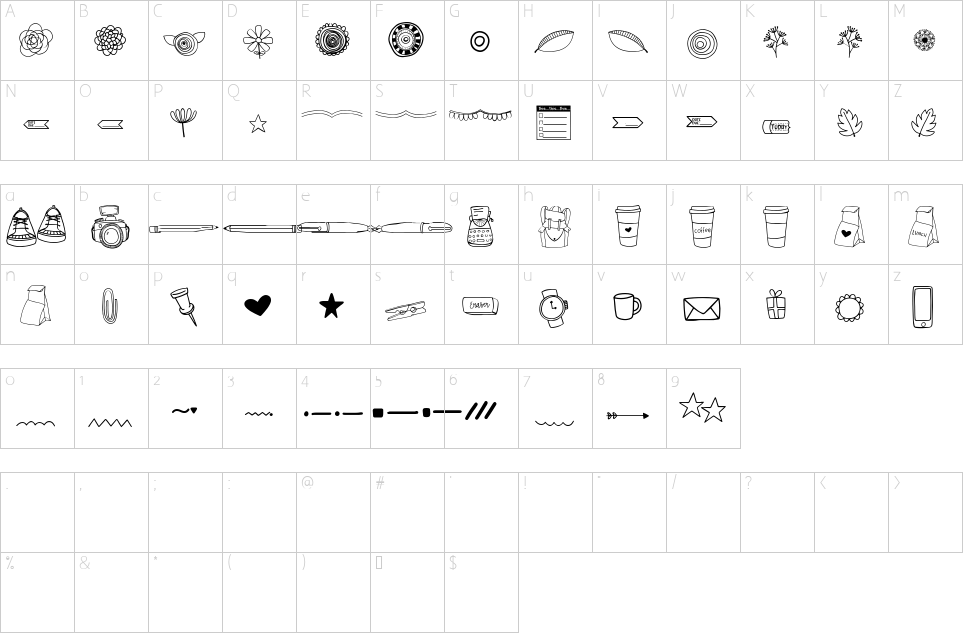
A Maggie Mae Doodles Font é uma fonte gráfica desenhada pela Groovy Journal Fonts, uma fonte divertida e criativa que vem para enriquecer qualquer projeto visual com seu toque de criatividade e charme. Esta fonte, disponível tanto para sistemas Windows quanto para Mac, foi criada para aqueles que buscam um estilo de desenho que transborda vida e energia, sendo especialmente atraente para projetos que incluem ilustrações, scrapbooking e artesanato. Com sua interface fácil de usar e estilo único, a Maggie Mae Doodles Font é a escolha perfeita para designers e criadores que buscam adicionar um toque especial a suas criações digitais. Descarregada mais de 5.772 vezes, esta font é uma opção de fonte que você não deve perder.